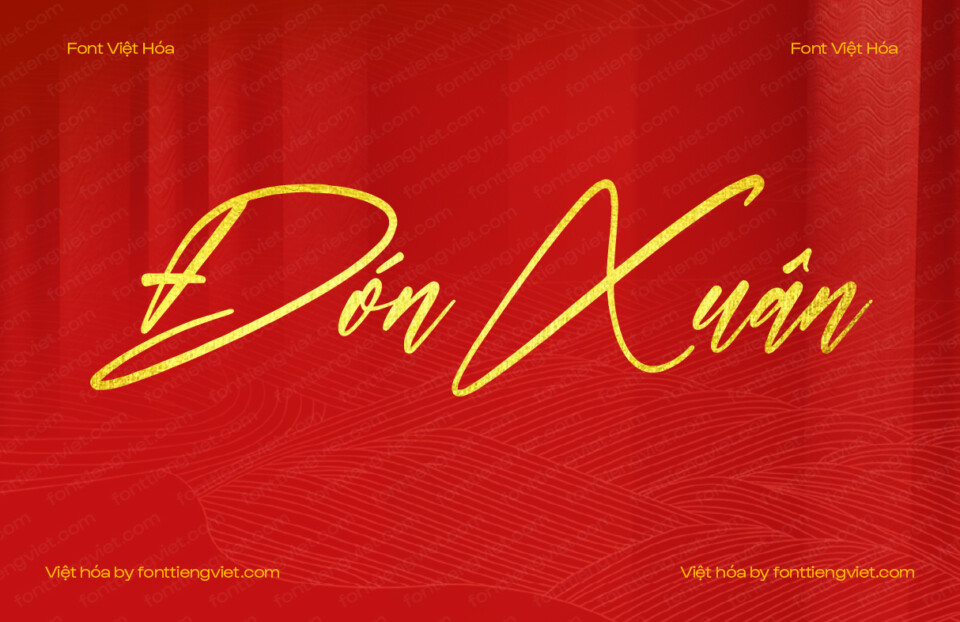
Giới thiệu về Font Việt hóa 1FTV VIP Archattson Hollmytro – Font tết
Mùa xuân đang cận kề, nhu cầu tìm kiếm các mẫu Font Chữ ấn tượng để trang trí thiệp chúc mừng, banner quảng cáo hay bao lì xì ngày càng tăng cao. Trong số đó, Font Việt hóa 1FTV VIP Archattson Hollmytro – Font tết nổi lên như một lựa chọn hàng đầu cho các nhà thiết kế chuyên nghiệp lẫn người dùng phổ thông. Đây là bộ font mang phong cách hiện đại nhưng vẫn giữ được nét tinh tế, sang trọng, cực kỳ phù hợp với không khí lễ hội truyền thống Việt Nam. Với các đường nét uốn lượn mềm mại và bố cục hài hòa, bộ font này giúp truyền tải thông điệp yêu thương một cách trọn vẹn nhất.
Tại sao nên chọn Font Việt hóa 1FTV VIP Archattson Hollmytro – Font tết?
Đặc điểm nổi bật của bộ font này chính là khả năng hiển thị tiếng Việt hoàn hảo, không bị lỗi dấu hay sai lệch ký tự. Điều này giúp các em học sinh và giáo viên dễ dàng sử dụng trong việc thiết kế bảng tin nhà trường hoặc làm bài tập sáng tạo. Sự kết hợp giữa nét bút dày dặn và thanh mảnh tạo nên sự tương phản thị giác độc đáo, giúp các dòng chữ “Chúc Mừng Năm Mới” hay “An Khang Thịnh Vượng” trở nên nổi bật và có hồn hơn bao giờ hết.
Cách ứng dụng Font Việt hóa 1FTV VIP Archattson Hollmytro – Font tết vào thiết kế
Bạn có thể sử dụng bộ font này cho nhiều mục đích khác nhau như làm tiêu đề cho video mừng năm mới, trang trí blog cá nhân hoặc in ấn menu cho các bữa tiệc tất niên. Nhờ tính linh hoạt cao, font chữ này không chỉ giới hạn trong dịp Tết mà còn phù hợp cho các sự kiện kỷ niệm quan trọng khác. Hãy kết hợp nó với những tông màu đỏ hoặc vàng đặc trưng để tạo nên hiệu ứng thị giác mạnh mẽ và ấm áp nhất.